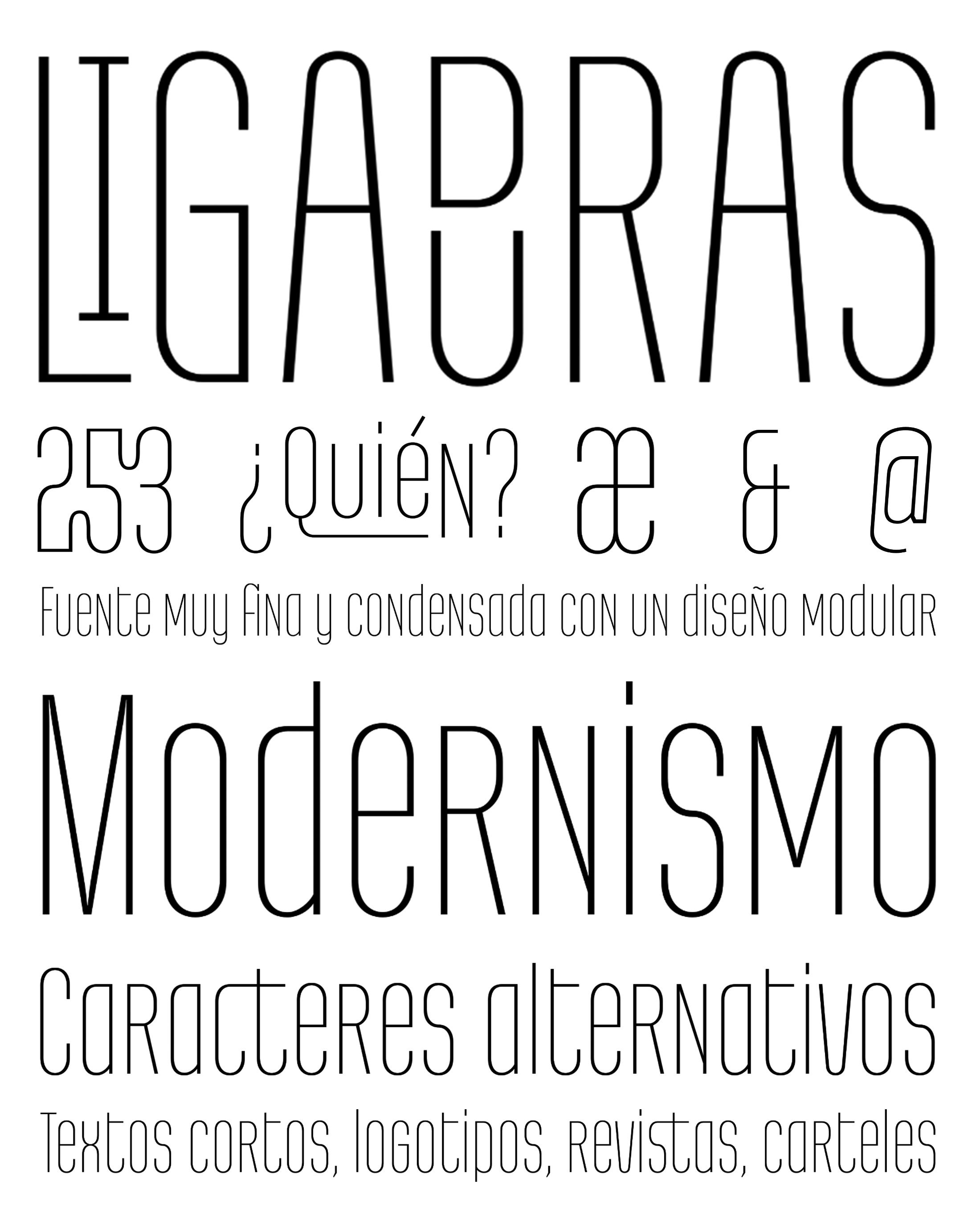
Regia Sans Pro
| Año | 2008 — Actualizada: ( 2011 ) |
| Créditos | Luciano Vergara |
| Descripción | La familia tipográfica Regia Sans Pro fue diseñada por Luciano Vergara y publicada por Latinotype. Regia Sans Pro contiene 1 estilo. Es una fuente muy fina y condensada con un diseño modular, muy adecuada para textos cortos, logotipos, revistas, carteles, etc |